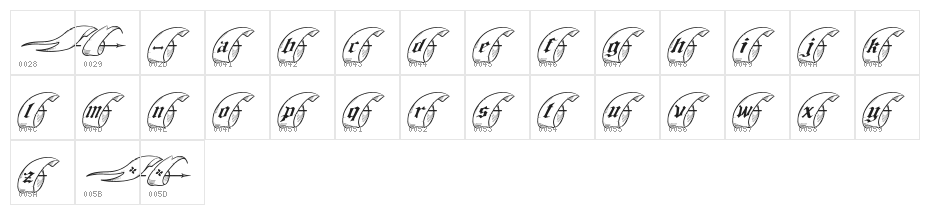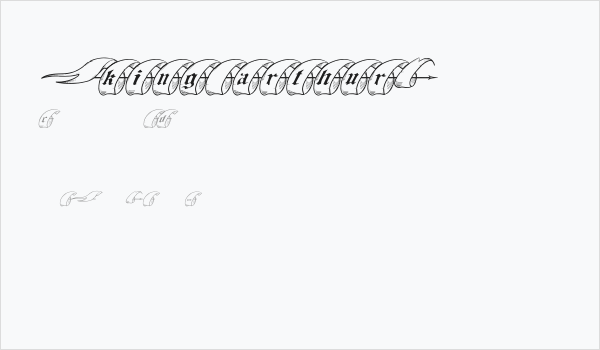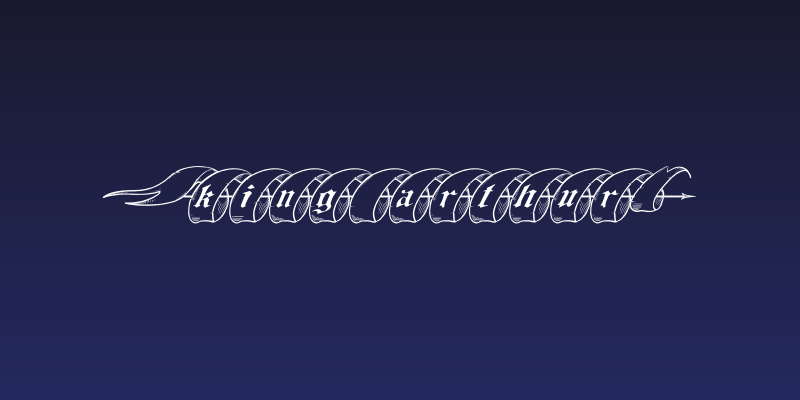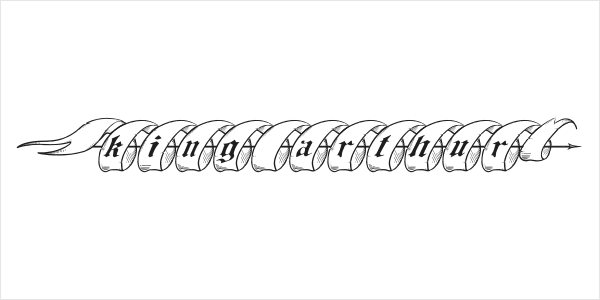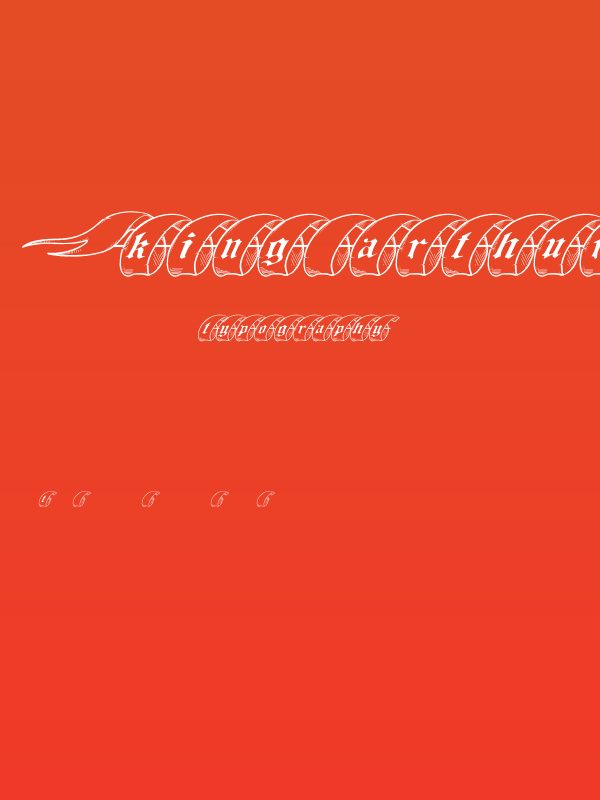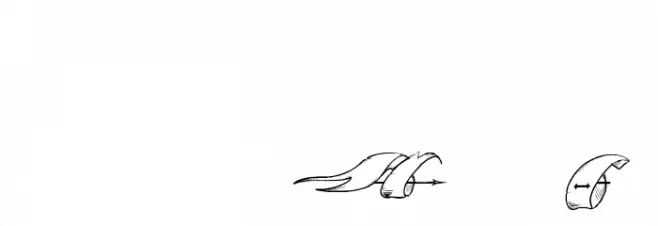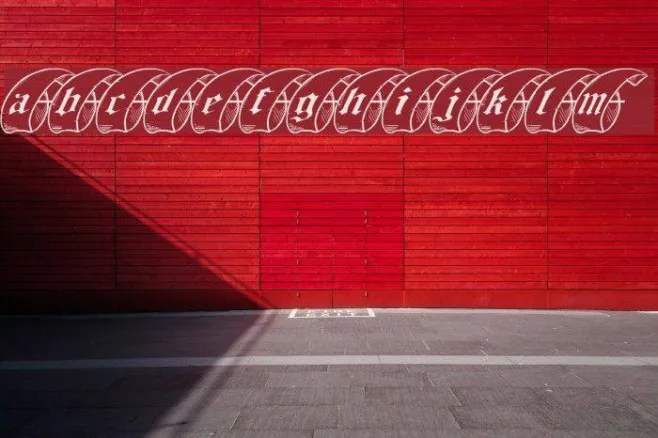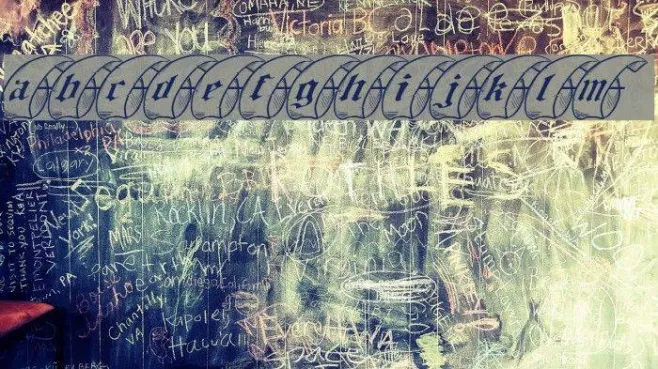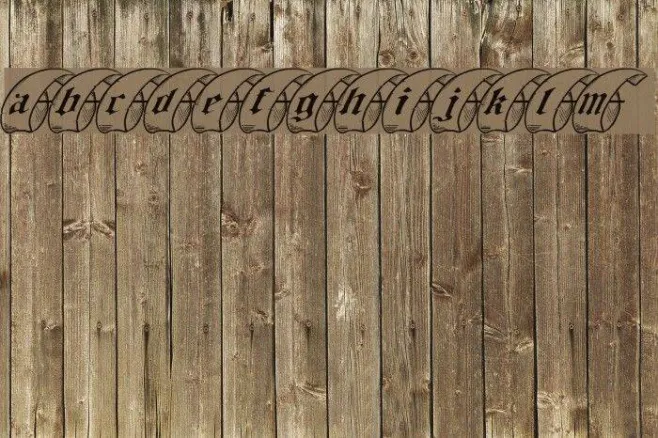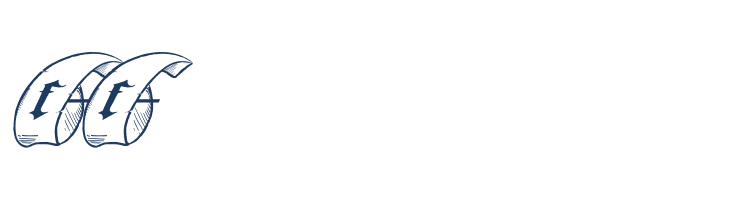
(KING ARTHUR) Font
✎ Gothic
| Categorías | Gothic |
| Estilo general | Vintage |
| Caso de uso | Logos, Headlines, Invitations |
| Proyectos propuestos | Ideal for historical-themed designs, fantasy book covers, medieval event invitations, or any project requiring a touch of elegance and antiquity. |